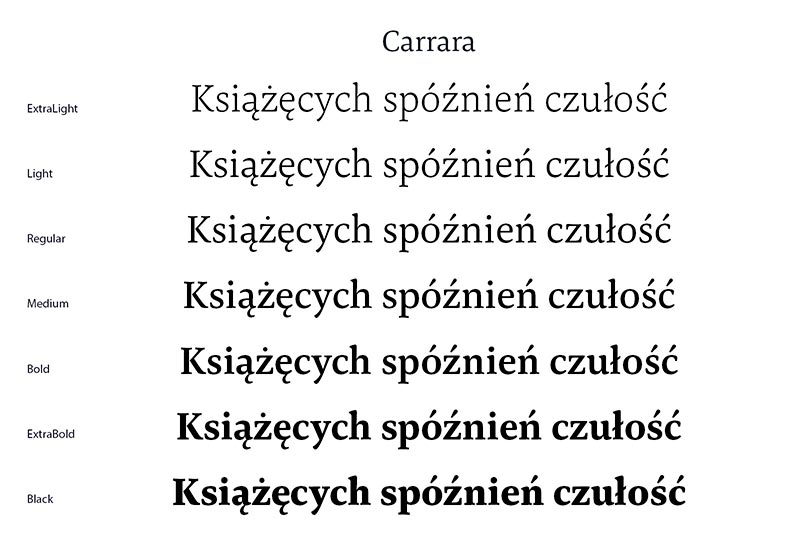
Font Carrara
Do naszego studia DTP trafił szeryfowy font Carrara, występujący w 7 odmianach grubości. Zaprojektowany w 2016 roku przez Dietera Hofrichtera font posiada polskie znaki diakrytyczne. Carrara znajdzie zastosowanie w projektowanych przez nas magazynach.